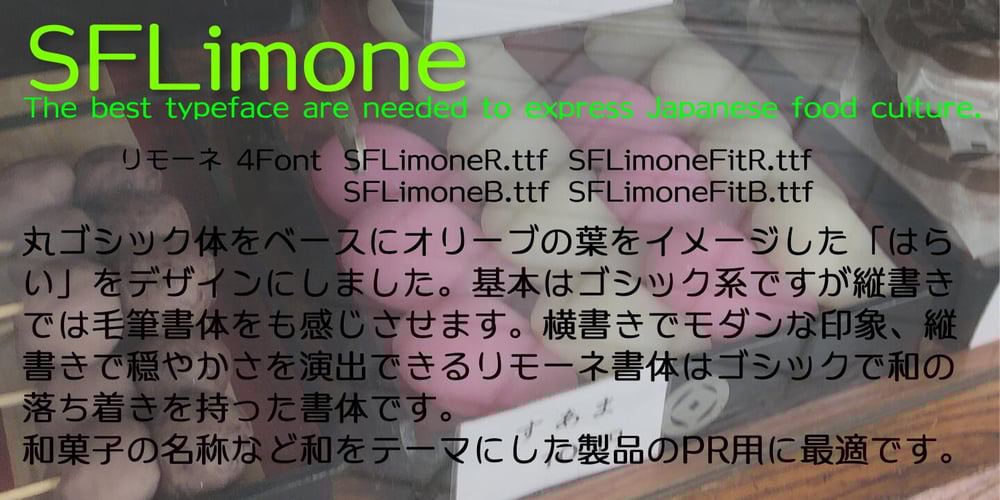
SF Limone Font Family was designed by published by Fonts66. SF Limone contains 4 styles and family package options. A feminine typeface with Japanese style features. 和風な特長を持った女性的な書体。 丸ゴシック体に毛筆タッチの曲線を組み合わせた、柔らかい印象が女性的でもあり、かつ和風のテイストも感じます。 和の名称や文章、カードなどに柔らかい表現にマッチします。